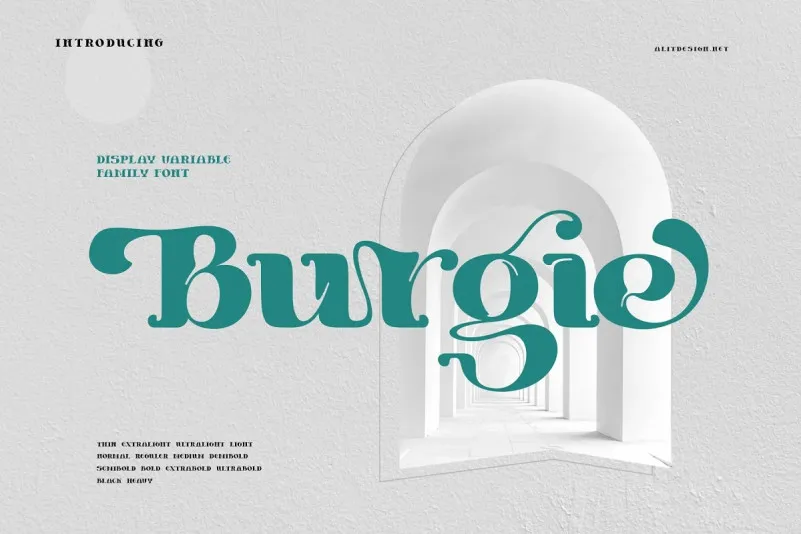
Burgie Black Serif Font – Download Grátis
A Burgie Black Serif é uma elegante fonte serif que surgiu da alit design, com seus traços leves até pesados. Esta fonte apresenta uma mistura de sofisticação e personalidade, criando um estilo único e distintivo, ideal para designs clássicos ou retro. Suas alternativas de giroswash tornam a escrita ainda mais interessante e única, tornando-a perfeita tanto para o design de posters quanto para design gráfico tradicional. Seja em uma revista de moda, um poster de festa ou até mesmo uma capa de livro de arte retro, esta fonte garante que seu trabalho seja notável e inovador. Ela é um ótimo complemento para qualquer projeto que valoriza a sofisticação moderna e o charme clássico.